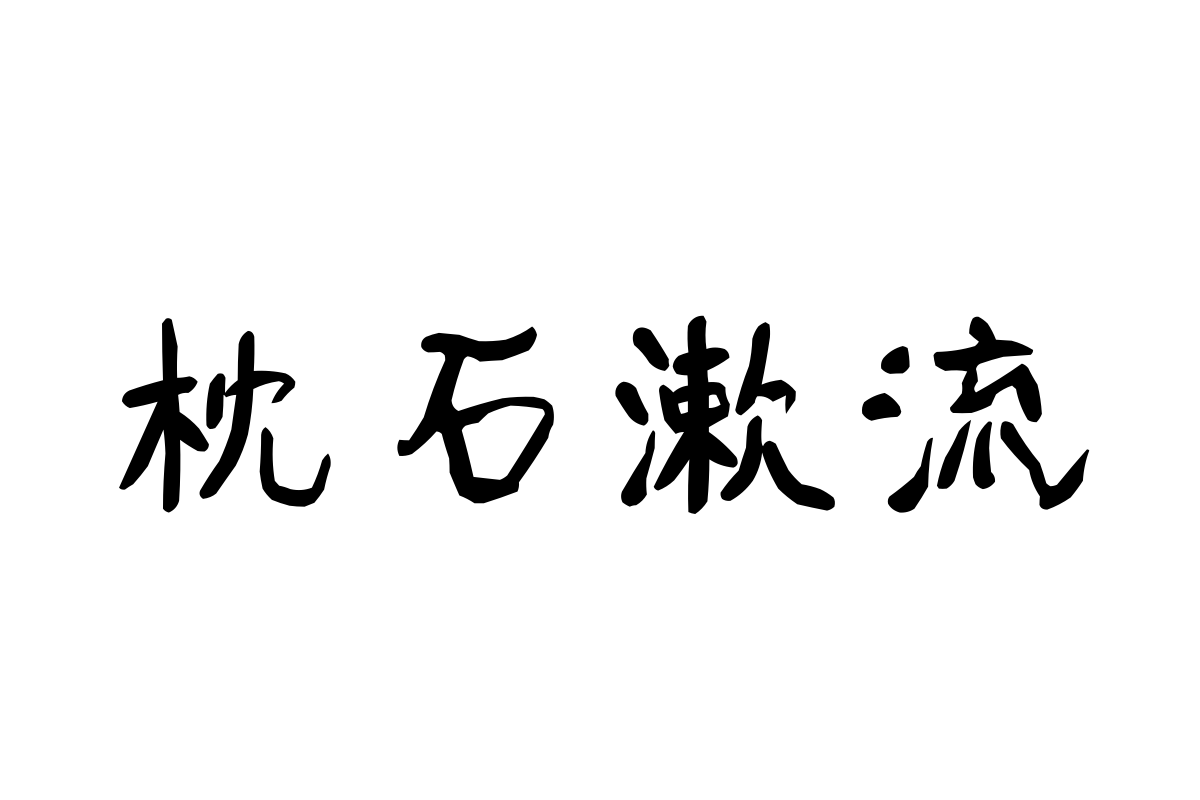
三极静静体是一种具有独特风格的字体,其特点是字形简洁、线条流畅。该字体适用于各种应用场景,如广告设计、网页制作、包装设计等。
三极静静体的笔画粗细适中,线条清晰,给人一种简约而不失美感的视觉体验。其结构紧凑,字形规整,易于辨认和阅读。同时,该字体也具有一定的可读性和易用性,适合用于正式场合的文字展示。
此外,三极静静体的设计风格独特,线条流畅,给人一种清新自然的感觉。它的应用范围广泛,无论是在商业还是艺术领域,都能展现出其独特的魅力和价值。